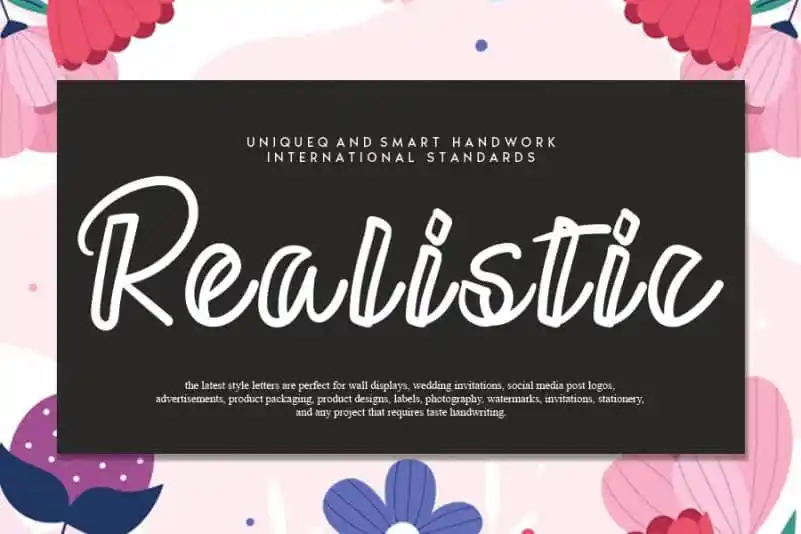
Realistic Script Font – Download Grátis
A fonte ‘Realistic Script Font’ é perfeita para quem busca uma transição suave entre a elegância do calligrafia e o frescor contemporâneo dos projetos digitais. Desenhada pelo designer andikastudio, essa fonte escrita à mão realista mantém os influentes traços de calligrafia enquanto se apresenta como um elemento que traz modernidade para qualquer projeto. É perfeita para aqueles que buscam um equilíbrio entre tradicional e contemporâneo em sua identificação visual, sendo a escolha ideal para criar textos com aparência sofisticada que destacam-se no design de uma maneira única. Seja para letras, logotipos ou qualquer outro tipo de conteúdo visual, essa fonte pode transformar seus projetos em verdadeiros trabalhos de arte, elevando-os ao topo da qualidade e elegância gráfica.